… in Marzahn-Hellersdorf!
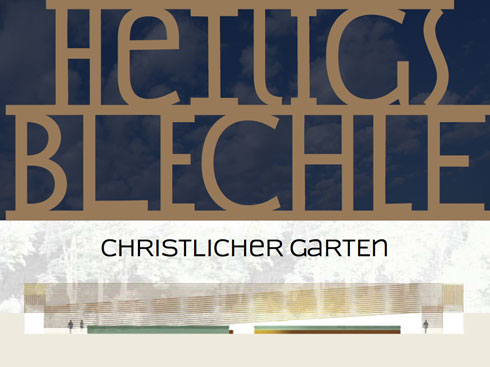
Gestern Abend war ich auf dem Berliner Typo-Stammtisch. Acht Designer stellten im Rahmen einer Pecha-Kucha-Session neue Projekte vor, darunter Alexander Branczyk (Xplicit Bln). Er berichtete über ein Projekt im Marzahn-Hellersdorf, das ich noch nicht kannte und das mir gestern wie gerufen kam. Nach der mittags hier im Fontblog veröffentlichten Schüler-Logo-Posse und den ersten zustimmenden Kommentaren war ich kurzzeitig verunsichert und fragte mich, ob es überhaupt noch professionelles (typo)grafisches Design im öffentlichen Raum gibt oder geben kann. Ja, gibt es. Sogar in Marzahn-Hellersdorf: Der Christliche Garten im dortigen Erholungspark. Und ich freue mich, heute darüber berichten zu dürfen.
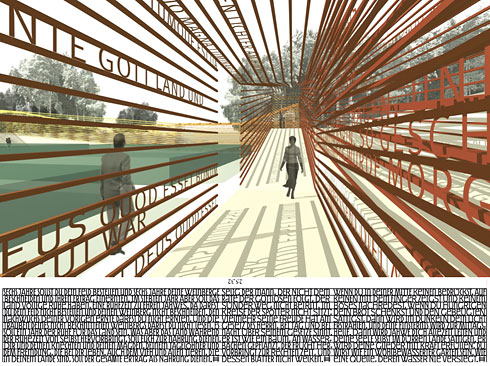
Der Erholungspark Marzahn liegt am nördlichen Fuß des Kienbergs und wurde am 9. Mai 1987 anlässlich der 750-Jahr-Feier von Berlin als »Berliner Gartenschau« und »Geschenk der Gärtner an die Hauptstadt der DDR« (Ost-Berlin) eröffnet. Mit den angrenzenden frei zugänglichen Erholungsflächen des Kienbergs und dem direkt östlich anschließenden Wuhletal ergibt sich eine Gesamtfläche von über 100 Hektar.
Zwei Jahre nach der Wende wurde die Anlage in Erholungspark Marzahn umbenannt. Spiel- und Liegewiesen kamen hinzu, Bäume wurden gepflanzt und Sondergärten eingerichtet. Seit Oktober 2000 ist der Park durch seine Gärten der Welt auch weit über die Stadtgrenzen hinaus bekannt. 2005 wurde der Chinesische Garten als drittschönste Parkanlage Deutschlands ausgezeichnet. Außerdem gehört der Erholungspark zu den 365 Orten im Land der Ideen.
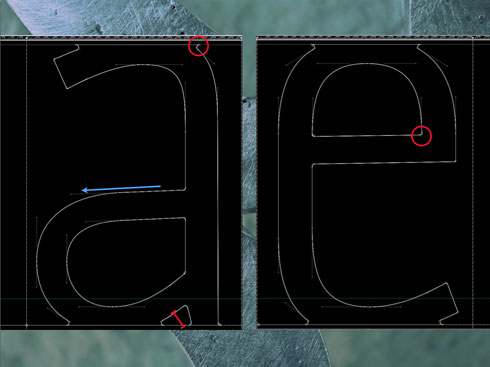
Nach dem Chinesische Garten (2000), dem Japanischen und dem Balinesischen (2003), folgten 2005 der mit Unterstützung der Allianz Umweltstiftung errichtete Islamische Garten. Inzwischen bereichern noch der Koreanische Garten, ein Irrgarten mit Labyrinth, der Karl-Foerster-Staudengarten und ein Italienischer Renaissancegarten die Gärten der Welt im Erholungspark Marzahn.
Seit 2007 laufen die Vorbereitungen für einen Christlichen Garten, die mit einem Planungs-Wettbewerb begannen. Eine hochkarätige Fachjury kürte schließlich den Entwurf des Berliner Büros Relais Landschaftsarchitekten zum Gewinner, der im Moment realisiert wird.
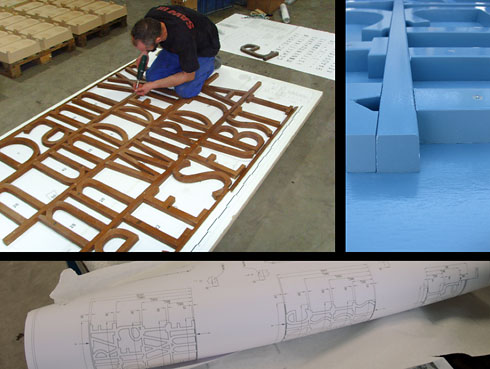
Abgeleitet von der Urform der Christlichen Gärten, dem klösterlichen Kreuzgang, entsteht in Marzahn ein »moderner« Klostergarten. Eine quadratische Gartenfläche mit einem Wegekreuz aus hellem Kies, Pflanzflächen aus Buchs und weiß blühenden Stauden sowie einem Wasserbecken, als Symbol für das Wasser als Quelle des Lebens.
Hauptattraktion des Christlichen Gartens wird der Wandelgang: Seine Wände bestehen aus goldlackierten Aluminiumflächen, in die Textpassagen aus dem Alten und Neuen Testament eingearbeitet sind. Damit wird daran erinnert, dass das Christentum eine Religion der Bücher und der Schrift ist.
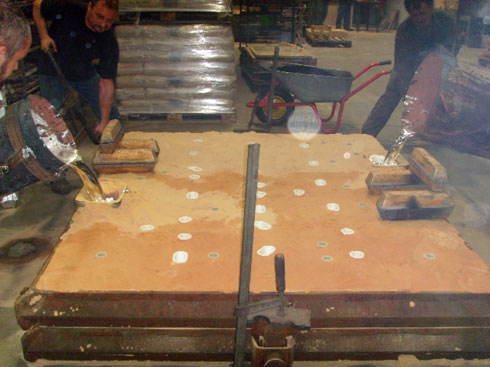
Die typografische Gestaltung hat Alexander Branczyk übernommen und gestern auf dem Typo-Stammtisch präsentiert. Die hier eingestreuten Abbildungen sind seiner Präsentation entnommen. Branczyk hat es sich nicht nehmen lassen, für das Projekt eine wunderbare exklusive Schrift zu entwerfen, deren Aussehen von der Aufgabe und der Herstellungstechnik bestimmt ist. Ganz nebenbei ist die Schrift zeitgemäß und unverwechselbar angelegt.
Die Buchstaben-Wände des Gartens werden aus gegossenen Aluminiumelementen gebaut. Die Herstellung der Lettern setzte dem Schriftgestalter einerseits Grenzen, andererseits nutzt er die verbleibenden Freiheitsgrade für spleenige Ausschweifungen. Das Ergebnis zeigt die einzigartige Qualität von Branczyks Schriftentwürfen, die er sich Anfang der 90er Jahre in Nachtsitzungen für das Technomagazin Frontpage angeeignet hat: für jede Ausgabe eine neue Headline-Schrift, darunter ging gar nichts. Schnell, zügellos, präzise – aber mit raffiniert kalkulierten Störungen … so möchte ich seinen Typostil charakterisieren.
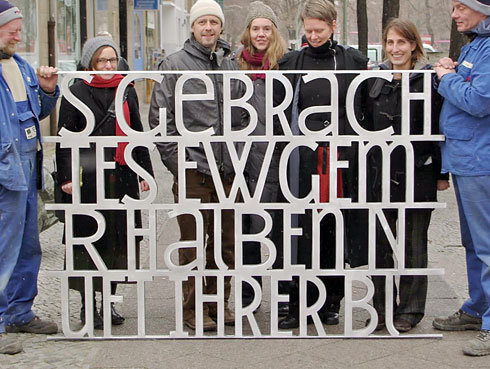
Nach ungezählten Test, Metallmischungen und Gussproben: Das erste Serienelement für die typografische Zitatewand des Christlichen Gartens im Erholungspark Marzahn (Alexander Branczyk mit Pudelmütze, Mitte)
Schönes Konzept, bravo!
Huch, irgendwie retro, fast Art Deco, trotzdem modern, trotzdem zeitlos. Gerade auf dem letzten Photos und den einzelnen Buchstabenskizzen sieht das aber echt gut aus. Congrats, Alex!
hallo alex, schöne arbeit!
Ja, das ist ganz interessant, obwohl es mich eher an Gefangensein als an christlich-inspiriertes Flanieren denken lässt.
Woran sieht man jetzt, dass es professionelles Design ist? Ich meine, das ist ganz gutes Design, habe aber nicht den Eindruck, dass alle, die da am Flexen und Philosophieren sind, auch dafür bezahlt werden.
Ganz einfach: gutes Design entsteht erst durch ein gutes Briefing. Logos für einen Stadtteil zu entwerfen, der keine bestellt hat, kann nur beliebige Ergebnisse bringen. Ein Corporate Design bei jovoto oder designenlassen bestellen, aber nicht in der Lage sein, das WARUM zu formulieren, kann nur nur beliebige Ergebnisse bringen.
Meine Verurteilung der Logo Posse Marzahn-Hellersdorf zielte nicht auf die Schüler und auch nicht auf die Qualität ihrer Arbeit – ich werde mich hüten, diese isoliert zu betrachten und zu bewerten: Ich habe ja kein Briefing als Maßstab in Händen. Sie zielt auf das System, so wie es jetzt von der Schule und von den Stadtverordneten inszeniert wird.
Letztlich ist es auch so eine Art Wettbewerb, wer bekommt die schönste Negativassoziation hin.